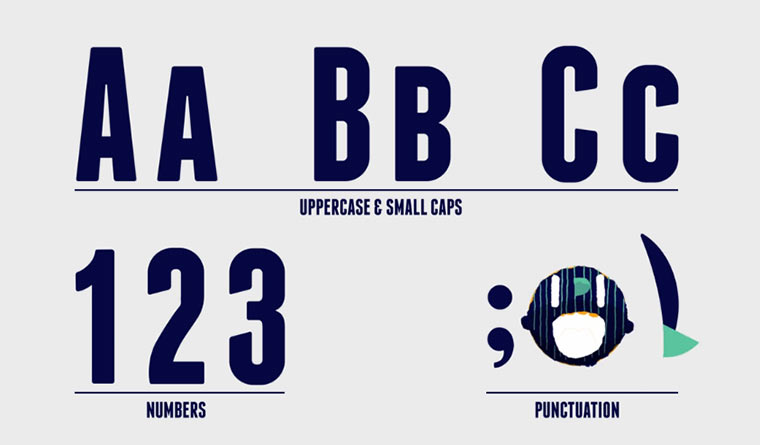
animierte Schriftart: Franchise
animierte Schriftart: Franchise FRANCHISE_01
25 Frames, 500×600 Pixel und vier Farben. Das waren die Vorgaben, die 110 Designer weltweit erhalten haben. Und die Möglichkeit, sich ein Zeichen auszusuchen. Und los ging es mit der Entstehung des Typfaces Franchise.
Anymography hatte zu der Aktion aufgerufen und heraus gekommen ist eine Schriftart, die verdammt kreativ animiert ist. Jeder Buchstabe (ob klein oder groß geschrieben) ist in total anderer Art und Weise animiert als die anderen. Aber stets stylisch und visuell ansprechend.
animierte Schriftart: Franchise FRANCHISE_02